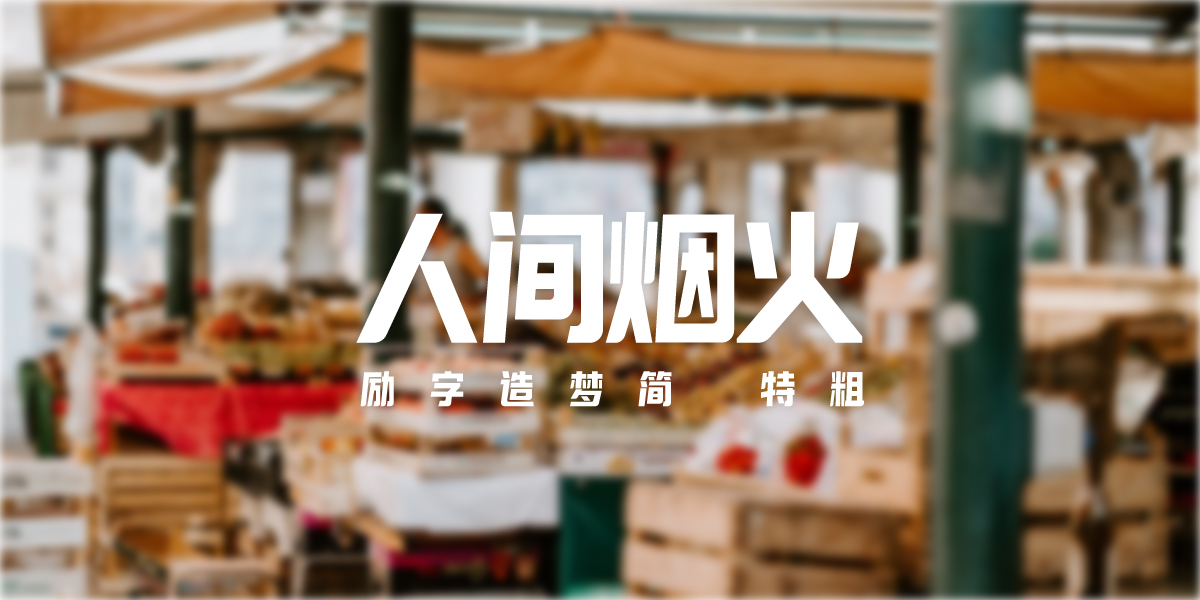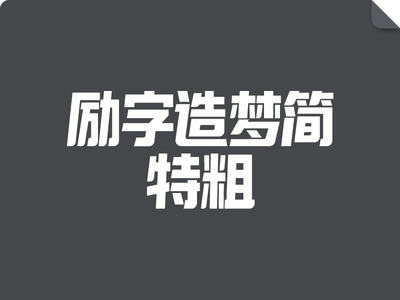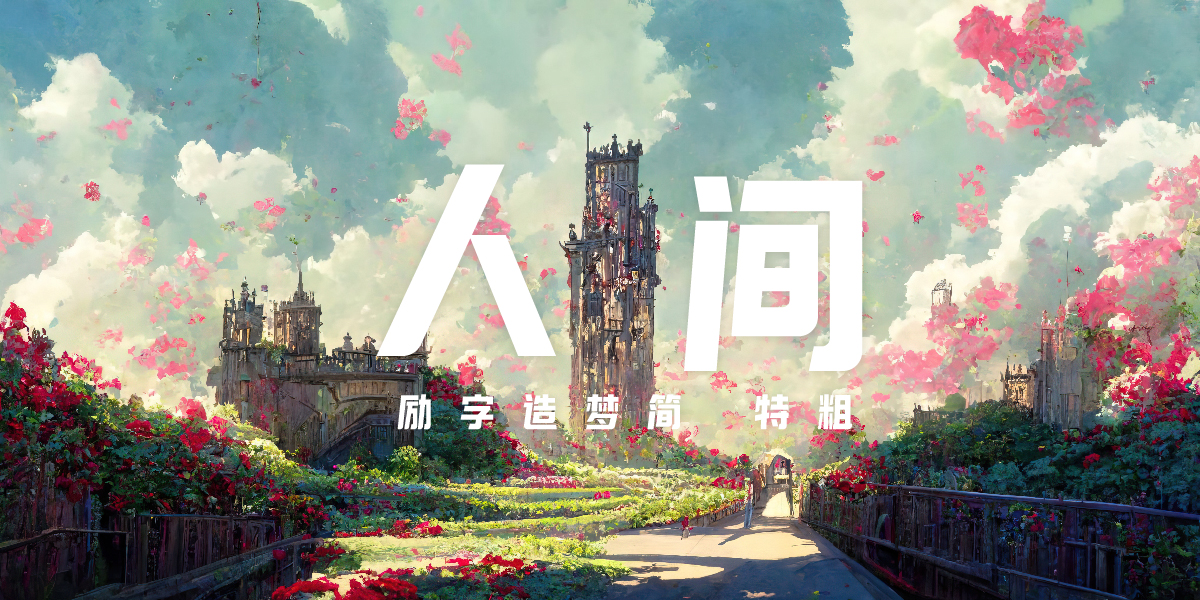
励字造梦简 特粗
励字造梦简 特粗,《励字造梦简 特粗(英文名Dream-PossibleGB-Black)》设计灵感来源于“青春筑梦”,左侧倾斜右侧竖直的不对称设计是字形的一大亮点,夸张的透视感模拟了建筑的宏壮,仿佛在城市之中抬头仰望摩天大厦。是基于对中文汉字的艺术热爱,创意设计出的一款独特字体,直线型字体,有力量感,棱角分明。字形轮廓清晰有力。